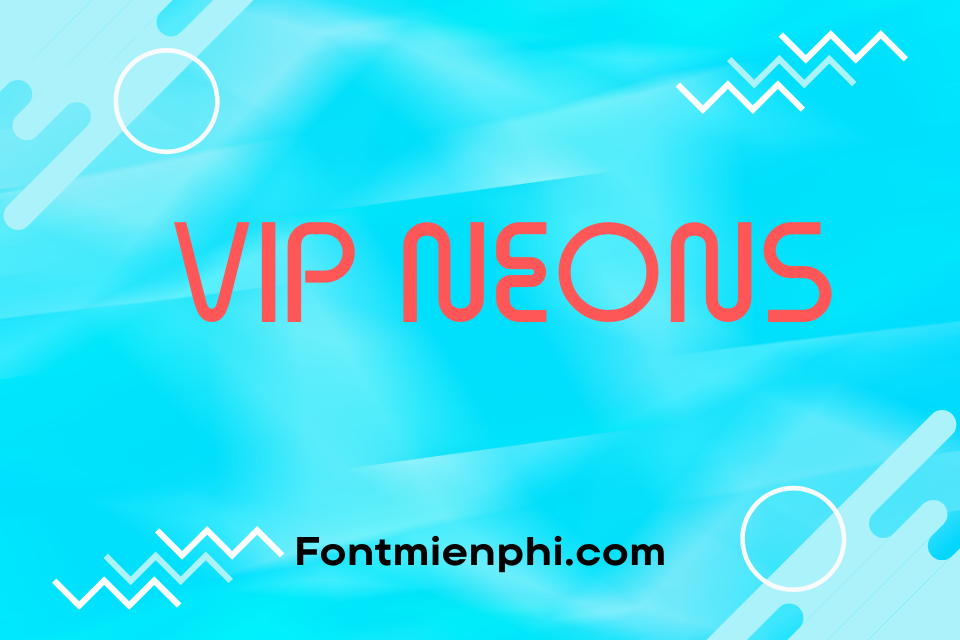
Font Việt hóa 1FTV VIP Neons
Về Font Việt Hóa 1FTV VIP Neons
Font Việt hóa 1FTV VIP Neons là một trong những font chữ đặc sắc, được thiết kế nhằm phục vụ nhu cầu sử dụng trong các dự án sáng tạo, quảng cáo và truyền thông. Với phong cách hiện đại và ấn tượng, font này mang đến sự nổi bật cho bất kỳ sản phẩm nào mà nó được áp dụng.
Đặc Điểm Nổi Bật
1. Thiết Kế Độc Đáo: Font 1FTV VIP Neons được thiết kế với các đường nét mềm mại, kết hợp cùng hiệu ứng ánh sáng neon, tạo ra một cảm giác sống động và thu hút. Điều này rất thích hợp cho các trang web, poster, hay banner cần sự chú ý từ người xem.
2. Tính Linh Hoạt: Font này có thể được sử dụng trong nhiều bối cảnh khác nhau, từ quảng cáo sản phẩm, sự kiện đến các dự án nghệ thuật. Sự linh hoạt trong thiết kế cho phép người dùng dễ dàng kết hợp với nhiều loại hình ảnh và màu sắc khác nhau.
3. Hỗ Trợ Tiếng Việt: Một điểm mạnh lớn của font 1FTV VIP Neons là khả năng hỗ trợ tiếng Việt. Điều này giúp người dùng Việt Nam có thể tạo ra các sản phẩm truyền thông mà không gặp phải vấn đề về hiển thị chữ cái. Font này bao gồm đầy đủ các ký tự, dấu câu và chữ cái tiếng Việt, đảm bảo sự chính xác và đẹp mắt.
Ứng Dụng Thực Tế
Font Việt hóa 1FTV VIP Neons rất phù hợp cho việc làm các mẫu thiết kế đồ họa, từ việc tạo logo cho đến các biển quảng cáo ngoài trời. Nó cũng lý tưởng cho các bài viết trên mạng xã hội, giúp tăng tính thu hút và tương tác từ người đọc.